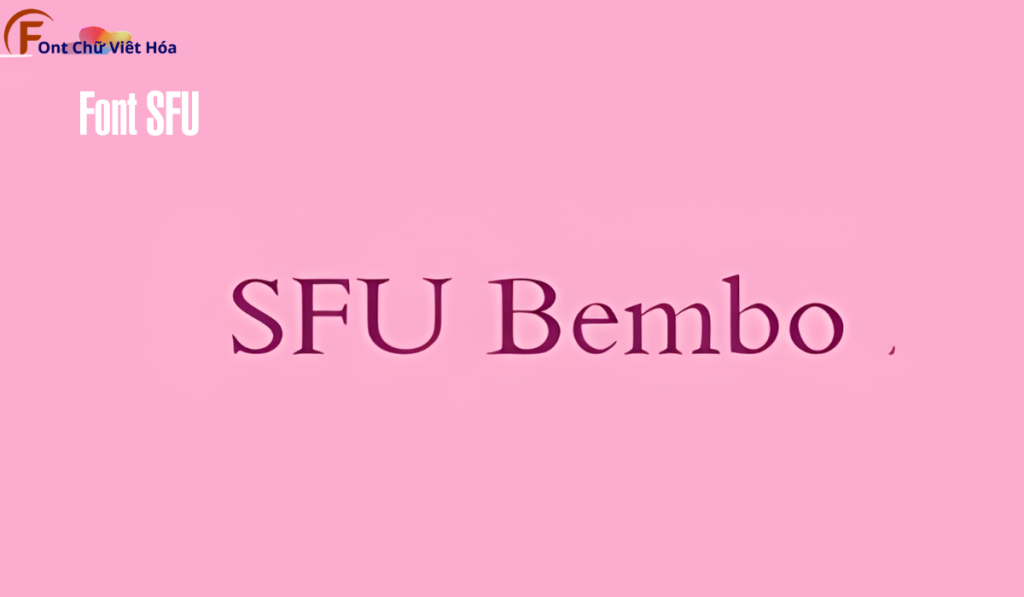
SFU Bembo Font Việt Hóa
Tác giả: Frederic Goudy
Ngôn ngữ: Tiếng Việt, Tiếng Anh
Bộ Font: SFU
Phân loại: Cổ điển
Độ dày: Regular, Italic, Bold, Bold Italic
Font SFU Bembo Việt Hóa là một font chữ độc đáo, mang phong cách serif cổ điển với các đường nét thanh thoát và tinh tế, thuộc bộ font SFU. Thiết kế của SFU Bembo tập trung vào sự sang trọng và dễ đọc, đặc biệt phù hợp cho các thiết kế đòi hỏi tính thẩm mỹ cao như sách, báo, và tài liệu. Với tỷ lệ chữ cân đối và các đường nét rõ ràng, font này tạo ra ấn tượng thị giác mạnh mẽ và giúp tối ưu hóa không gian trong thiết kế. Font này cũng đã được Việt hóa, mang đến sự linh hoạt và tiện dụng cho các dự án thiết kế bằng tiếng Việt.